1、思源字体
拥有ExtraLight/Normal/Regular/Medium/Bold 和 Heavy七款字重,广泛应用于广告设计、名片设计、包装印刷、产品设计等应用。其中有思源黑体、思源宋体、思源柔黑体。
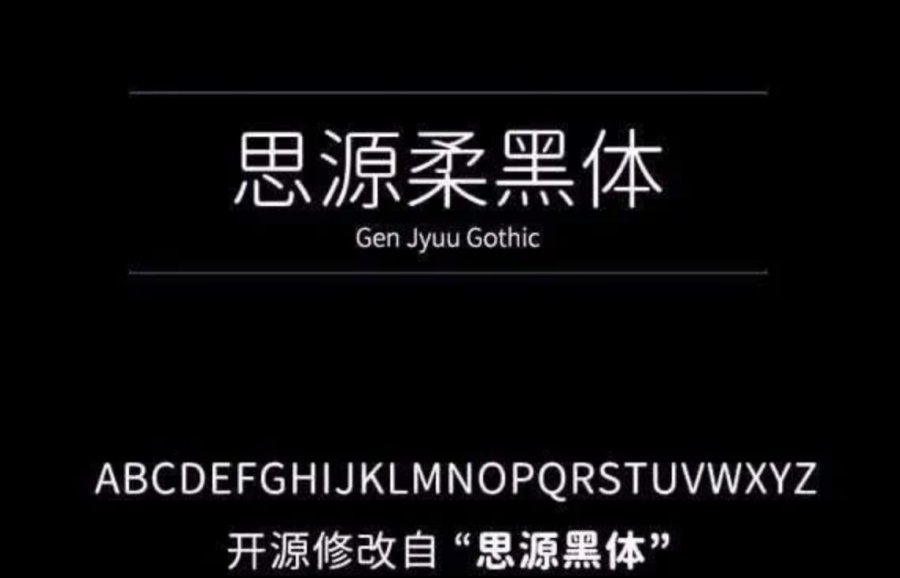
2、旁门正道字体
庞门正道字体至今发布了三套免费字库,分别是庞门正道轻松体、庞门正道粗书体、庞门正道标题体。
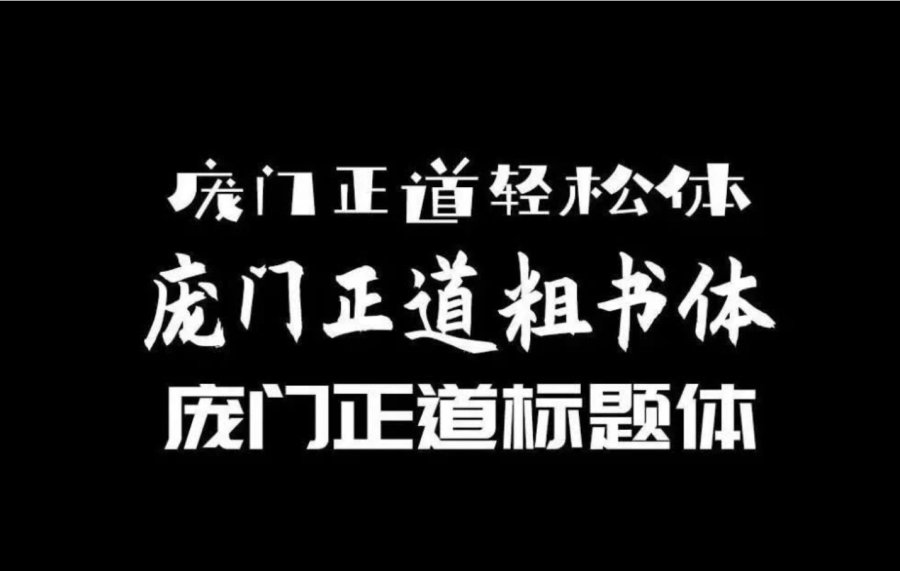
3、优设标题黑
该字体平稳、速度、有力量。在设计海报的时候又多了一款免费好用的标题字体。
标题用得最多就是这款字体啦
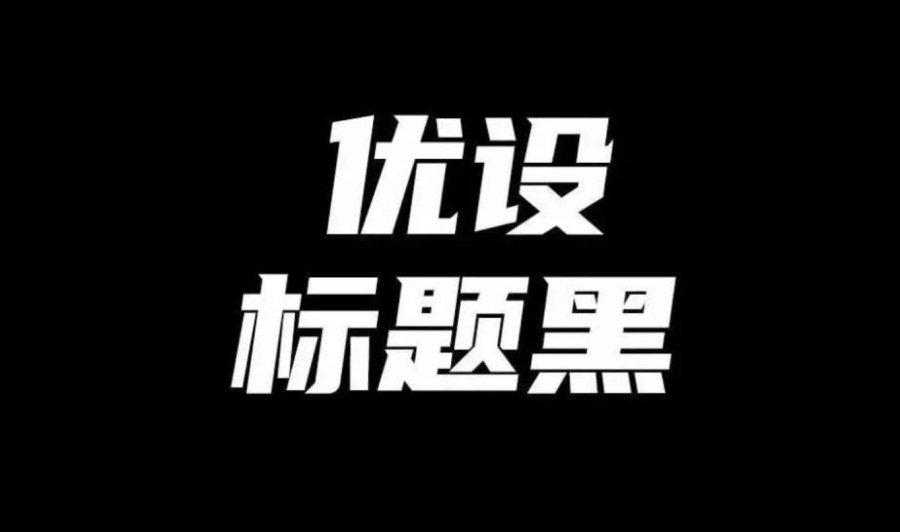
4、站酷字体6款
由站酷网联合站酷上的字体设计师们一起设计发布供广大网友免费使用,分别是站酷酷黑体、站酷文艺体、站酷庆科黄油体、站酷小薇LOGO体、站酷快乐体、站酷高端黑。这些字体风格覆盖面广,极具创造力,使用场景非常全面。有诙谐可爱型也有伶俐直角型,任何风格都能hold住。
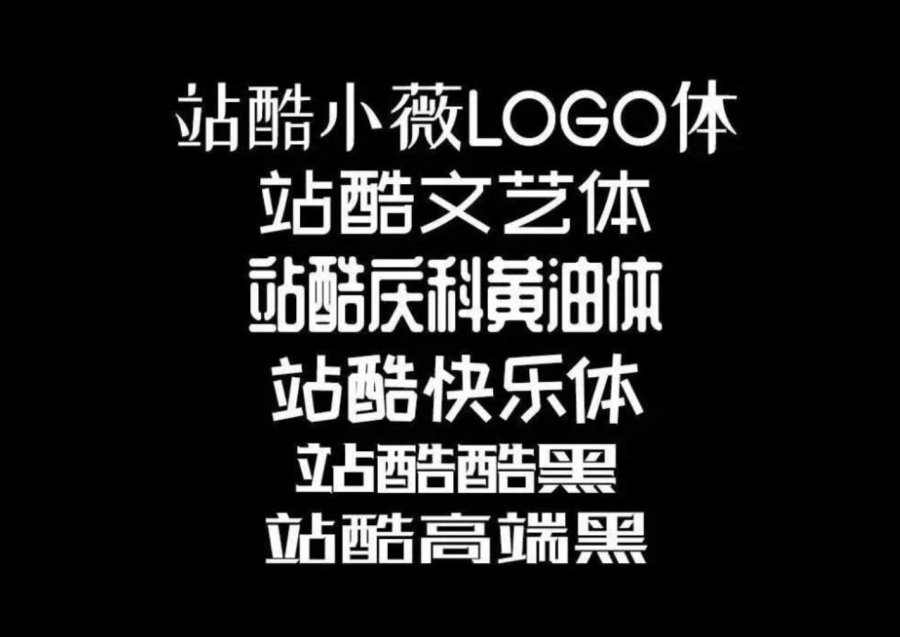
5、锐字真言体
笔触浑厚有力,笔画曲折有度,字形个性鲜明,刚柔并济,直角与圆角的错落搭配使得字体婉转有度,落落大方,给人以道劲有力、端正凝练的感受。
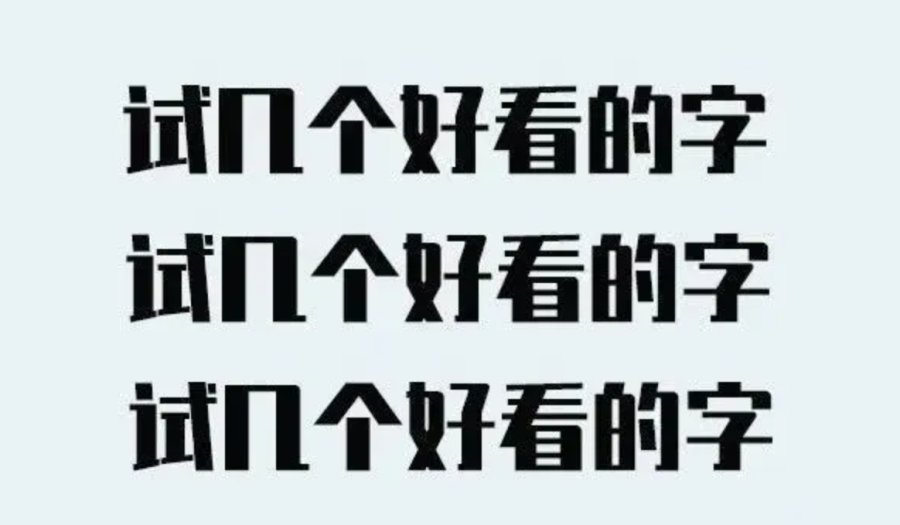
6、联盟起艺卢帅正锐黑体
由设计师卢帅与集合众多学员、设计讲师一起设计完成的一款免费商用字体。字体笔触粗实,字形厚重有力,是一款非常刚性,设计感很强的标题字体。
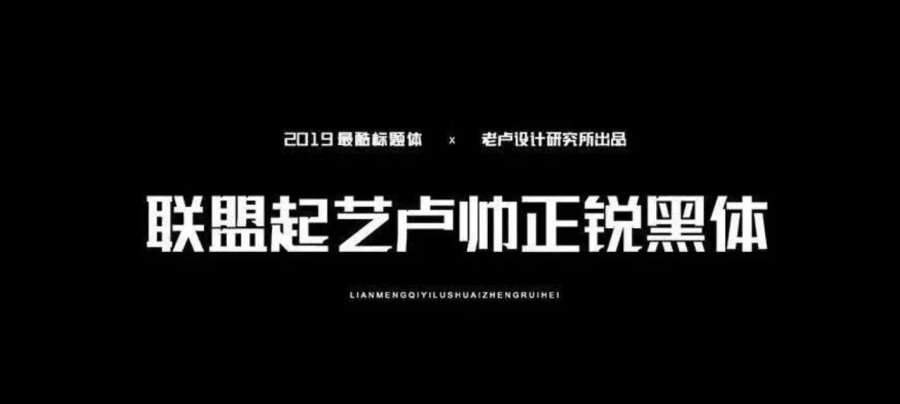
7、包图小白体
包图小白体原名“小白体”是由字体视界2018年制作的一款字体,为了让更多的免费字体为设计师所用,包图网与字体视界合作将该字体公益开源,供大家免费商用。
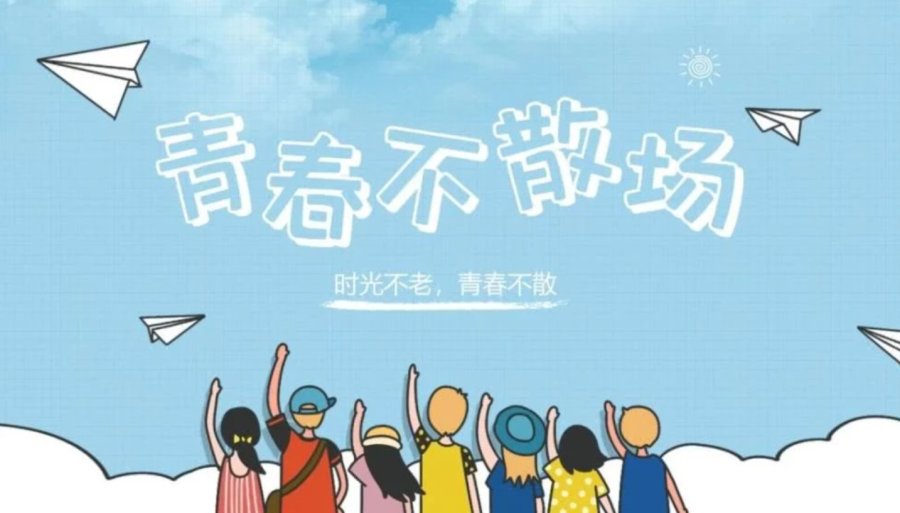
8、贤二体
汉仪贤二体是汉仪字库联合北京龙泉寺动漫中心联合设计的一款佛系字体。字体组合结构松散,重心不稳,字形偏长,起笔收笔锋利且粗细对比明显,笔画笨拙微带曲线感,具有谐幽默的效果。
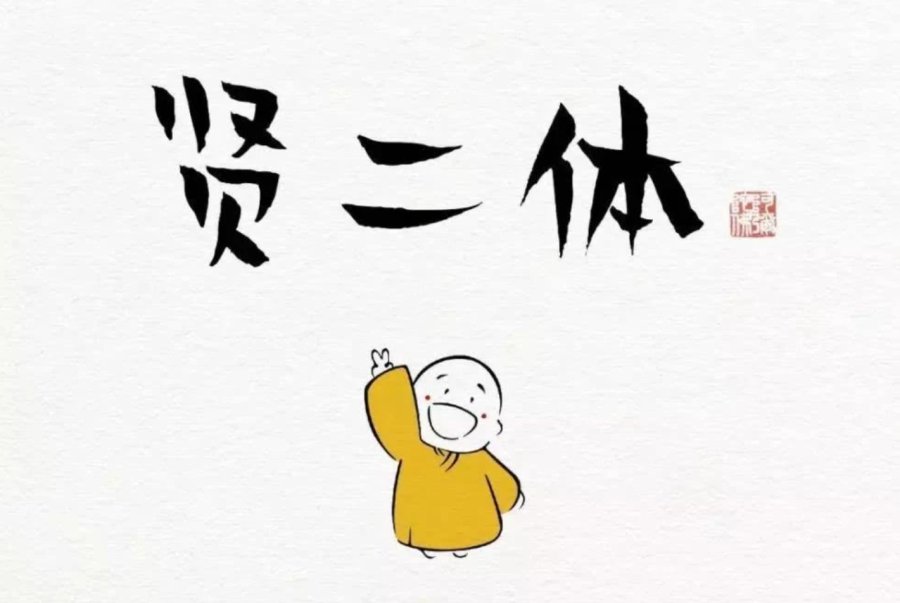
9、沫瑶手写体
是设计师春颜秋色原创的偏可爱风格手写字体。这款字体以设计师女儿名字命名,是送给女儿的礼物,也是送给大家的字体。(字体在软件显示的名称为:Muyao-Softbrush)
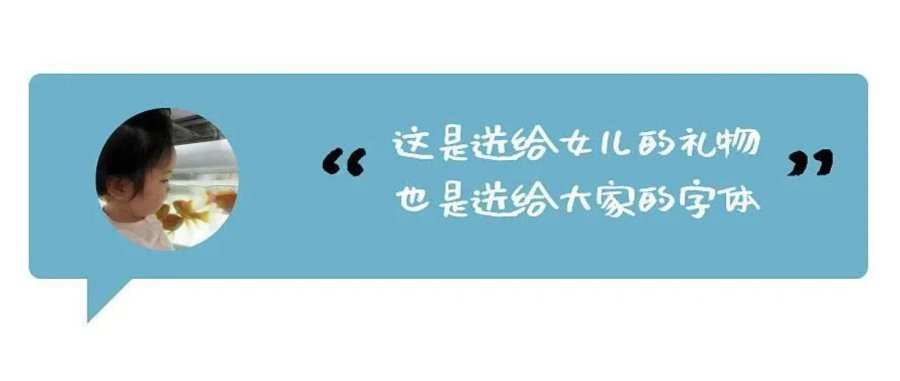
10、杨任东竹石体
该字体笔画道劲灵动,连笔张弛有度,结体清丽优美,如诗般优雅洒脱,整套字体有7个字重,字体按照GB2312-80书写,并增补了少量常见汉字。
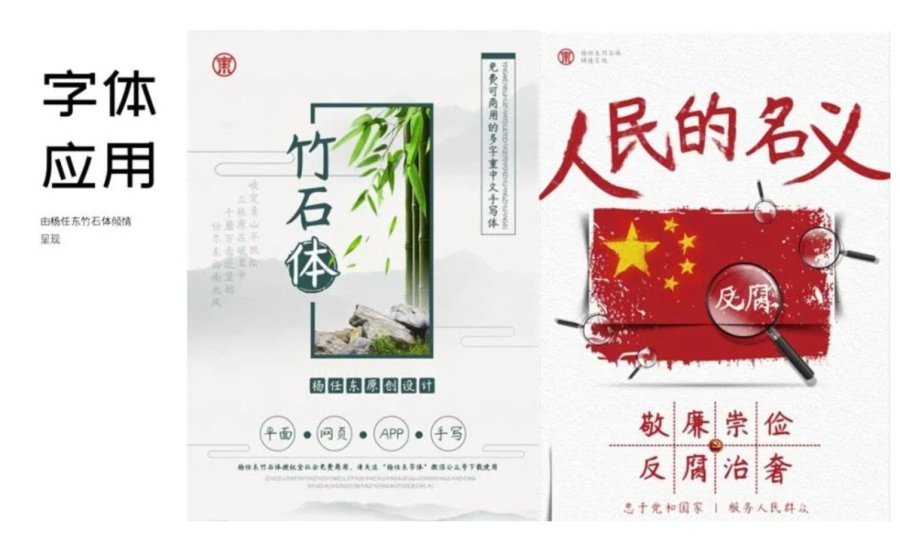
11、赖户字体
赖户字体,是一款偏可爱风的字体,由日本的一位业余字体设计师所制作的。比较难得的是支持中文简体,而且缺字较少。
12、装甲明朝体
基于思源宋体衍变而来,将横变得更细
整体更有科技力量感。